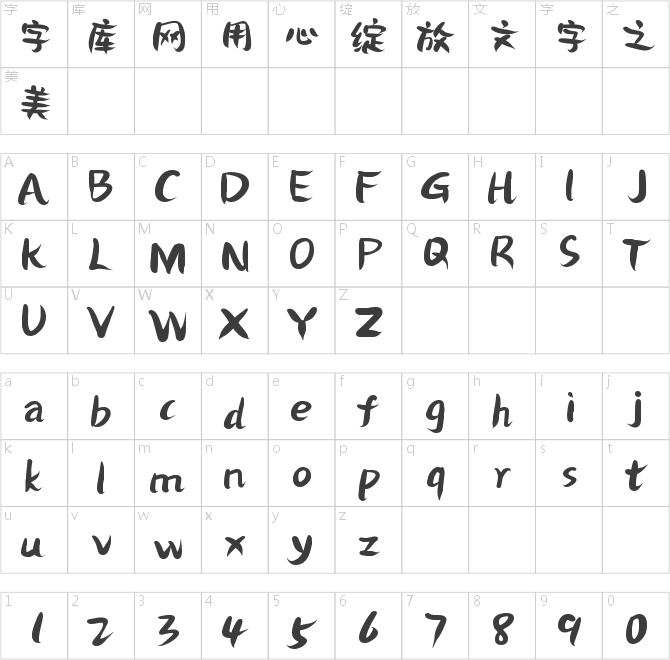
字魂258號-兒歌體是一款可愛的創意字,該字體筆畫呆萌隨意,非常的養眼,創意十足,可以廣泛應用于名片設計、包裝設計、網頁設計、新聞媒體、宣傳海報、ppt、影視制作以及內容用字等領域。
字魂258號-兒歌體字體ZiHun258Hao-ErGeTi字庫是一款讓人賞心悅目、百看不厭的中文字體,適合各類廣告和產品包裝設計應用,字體大小12.63MB,格式為ttf字體,上傳用戶是張海燕吶,作者/版權方為字魂